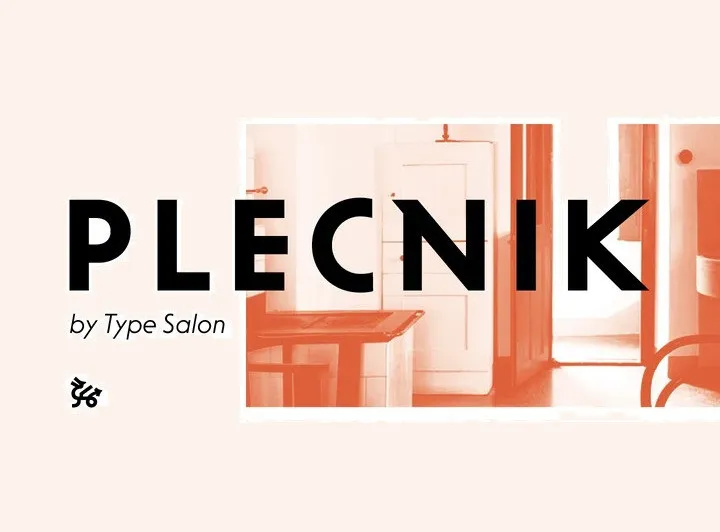
A fonte Plecnik é uma versão sans-serif que surgiu a partir do trabalho de Jože Plečnik, famoso arquiteto sloveno cujos designs arquitetônicos e gráficos têm muitas influências em sua criação. Esta nova fonte mantém o equilíbrio formal e elegante da serifada, mas apresenta uma aparência simples e limpa. Ela segue as leis e princípios de Plečnik ao criar um legado tipográfico rico, ainda não descoberto pela comunidade global, inspirando novas gerações de designers a explorar e valorizar os diferentes aspectos da arquitetura e design gráfico. Esta fonte é uma excelente opção para quem busca elegância formal em desenho sem linhas serifadas ou quer explorar um novo estilo que ainda mantém o brilho visual característico do trabalho de Plečnik.